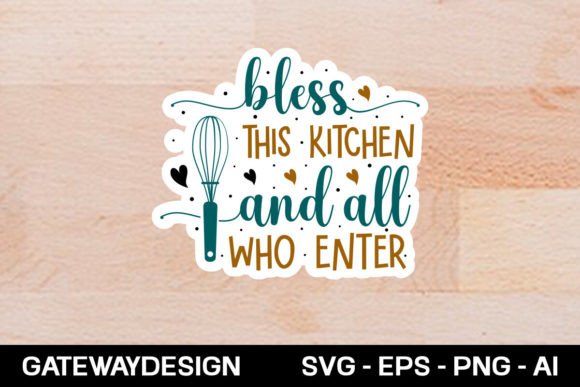
Bless This Kitchen and All Who Enter
Encontrar os elementos de design certos pode ser um desafio, mas Bless This Kitchen and All Who Enter oferece uma coleção excepcional que eleva o seu trabalho instantaneamente.
Trabalhado com precisão, Bless This Kitchen and All Who Enter fornece vetores limpos, tipografia suave e uma licença comercial para sua tranquilidade.
Quer você esteja criando produtos POD (Print on Demand), convites de casamento ou gráficos para mídias sociais, Bless This Kitchen and All Who Enter é a escolha ideal.